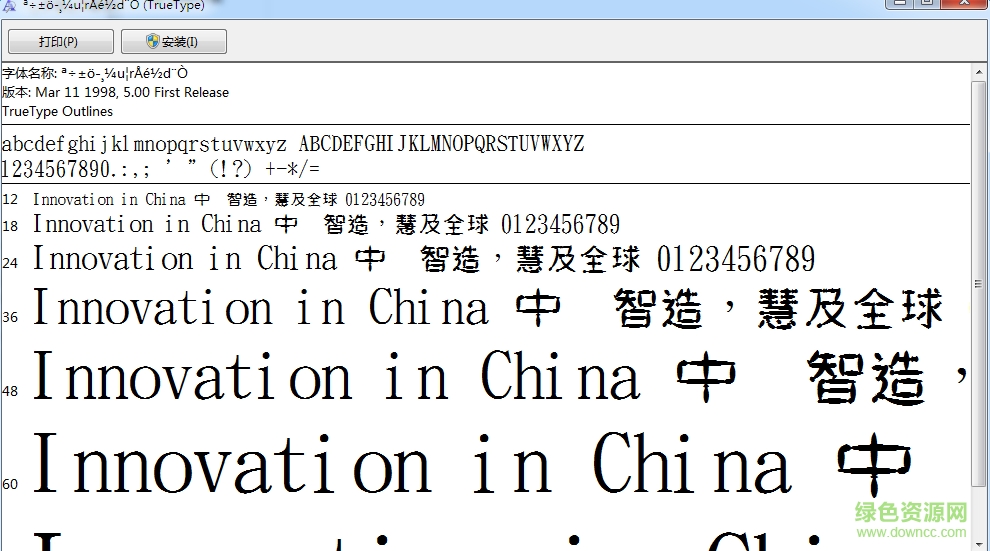
金梅飛彈字體范例是一款看上去非常有特點(diǎn)的電腦字體,輸入中文的時(shí)候,你會(huì)發(fā)現(xiàn)字體的筆畫(huà)好像是子彈飛過(guò)去留下的痕跡一樣,感興趣的朋友歡迎來(lái)綠色資源網(wǎng)下載試用!
審美要比黑體的高雅很多。在海報(bào)與網(wǎng)站圖標(biāo)中運(yùn)用比較多,不適合做正文和標(biāo)題的選擇,比較適合副標(biāo)題文字的選擇。